文字大全是我们在写字、写文章的好帮手,有一本字体下载大全在手就掌握了中华民族博大的文字文化。字体视界公司的文字大全一定会是你想要的。
字体视界给你相对较全的文字大全,该网站的字体大全有简笔和繁体两种,总有一款是符合你需求的。字体视界的文字大全有太多种类的文字形式了。
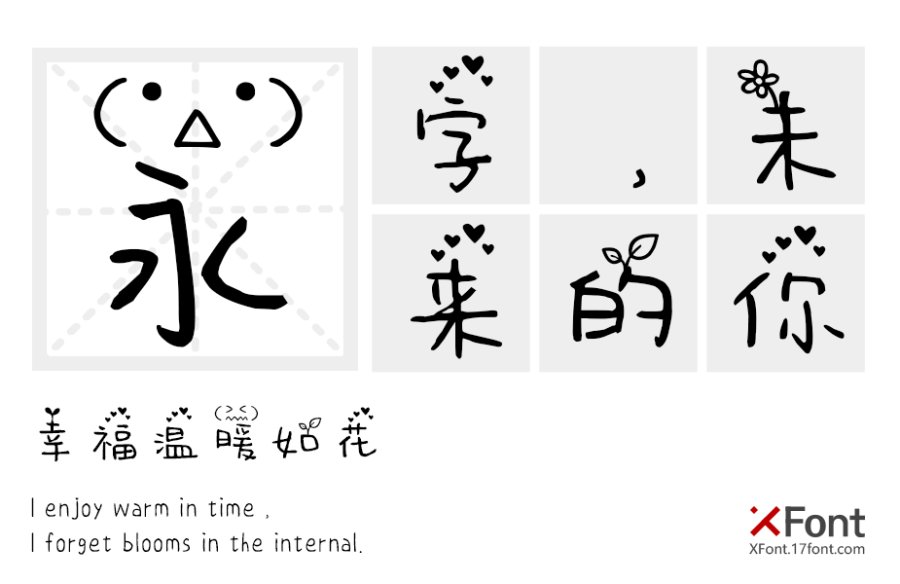
字体视界的文字大全有它自身的特点和优点,它与其他不同的文字大全来相比较的话,它比较高端且性价比更高,因为就其字体设计风格来说,有符合各种追求文章总体品质的小而美的字体设计,也有追求篇幅大的大而圆的字体风格,各式各样,任君选择。
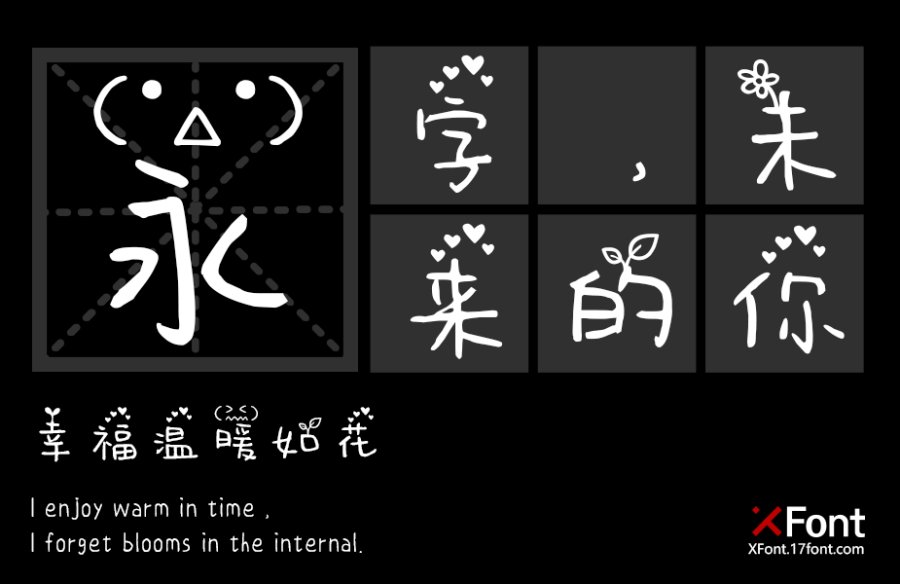
再者,文字大全并不只有汉字的存在,还有其他国家的字体,若你感觉单单看字体觉得乏味无比的话,字体视界又能给你比较好的解决方法了,设计师已经在文字大全的文字旁边设计了相应的图片,通俗又易懂,简直是不要太过贴心呢。